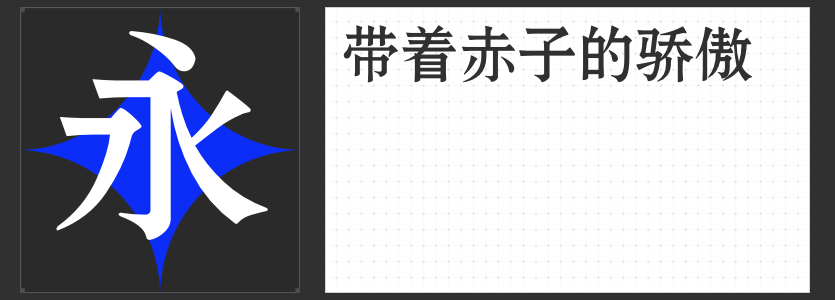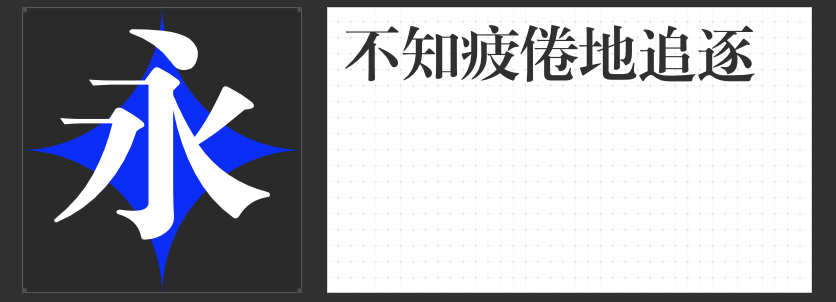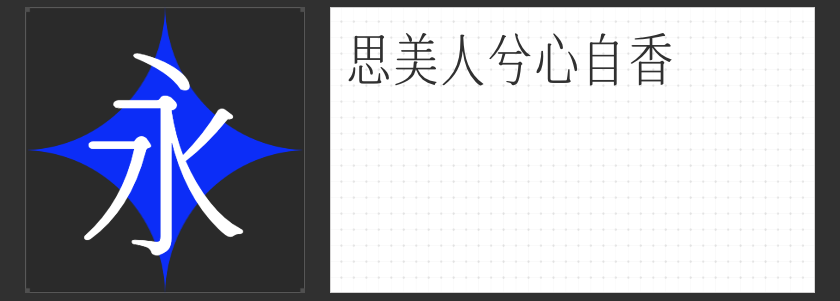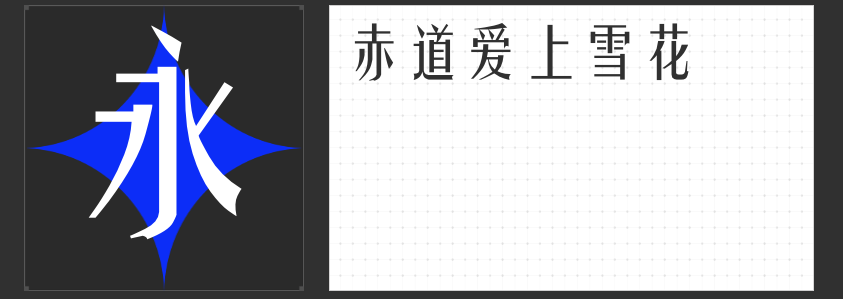
展览之美:四款精选字体打造独特博物馆体验
博物馆是连接过去与未来的桥梁,是展现文化多样性的窗口。在这里,每一件展品都有其独特的故事,每一次展览都是一场视觉盛宴。为了更好地呈现展品的魅力,字体的选择变得尤为重要。下面这些字体各具特色,能够为展览增添不同的氛围。
1. 励字小标宋简
“励字小标宋简”是一款极具美感的字体,它保留了宋体字的典型特征,线条流畅而优雅。这款字体适合用于博物馆快闪展览的海报设计,能够迅速吸引参观者的注意。它的简约风格不仅能够突出展品本身的重要性,同时也为整个展览空间营造出一种时尚与经典的结合气息。
2. 字圈也字思美人宋体
“字圈也字思美人宋体”是一款复古且充满故事感的字体。设计师在宋体架构的基础上加入了极为精致纤巧的衬线,使得每个字都显得修长秀美。这种字体非常适合用来制作展览物品的简介海报,能够帮助观众更深入地了解每件展品的历史背景和文化意义。它所蕴含的独特韵味,仿佛能将人们带回那些遥远的时代,感受历史的温度。
3. 励字姚体简繁
“励字姚体简繁”是一款结合了黑体的刚劲与扁平,以及宋体的规整特点的字体。它的笔画粗细适中,既有力量感又不失细腻之处。这种字体非常适合用于展览的导览牌或者重要信息的展示,能够让参观者在短时间内捕捉到关键信息。同时,它还能展现出展品的庄重与典雅,增强展览的整体艺术感。
4. 励字宋黑简
“励字宋黑简”是一款以黑体为原型,融合了宋体特点的字体。它拥有端正大方的字形结构,横竖笔画挺拔有力。这种字体适用于展览的主题介绍或是宣传资料的设计,不仅能够凸显展览的现代感,还能确保信息传达的清晰性。它简约而不简单的设计风格,能够有效地提升展览的整体品质,给参观者留下深刻印象。
字体虽小,却能大大影响展览的氛围和观感。上述四款字体各有千秋,它们不仅能为博物馆展览增添独特的艺术魅力,还能让参观者在欣赏展品的同时感受到文字本身的美。希望您在下次策划展览时,能够从中找到最合适的那一款,共同创造一场难忘的文化盛宴。